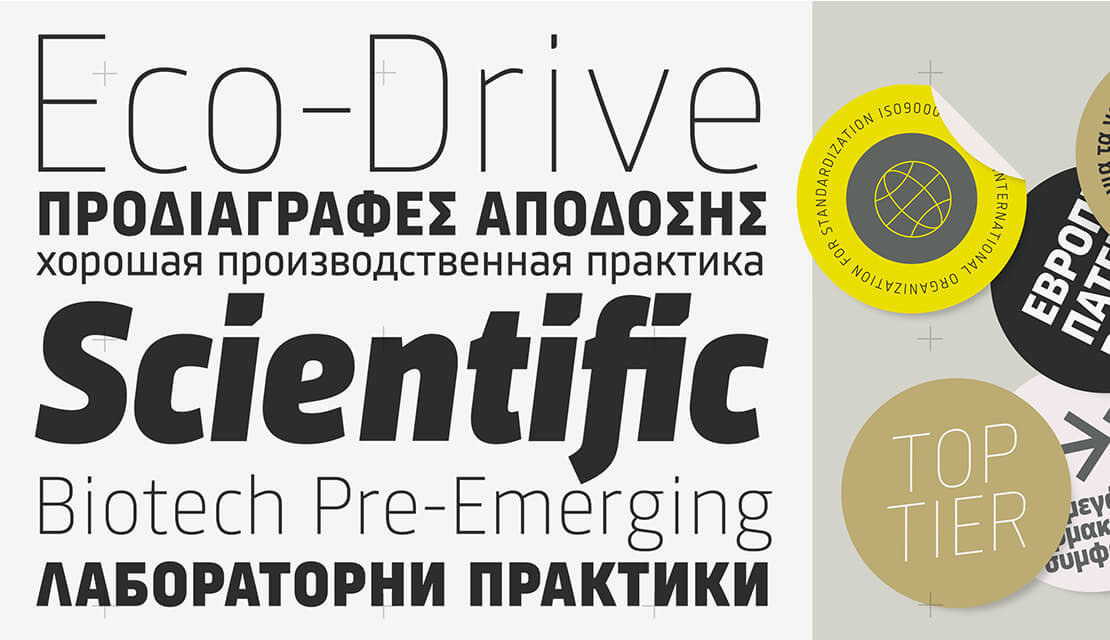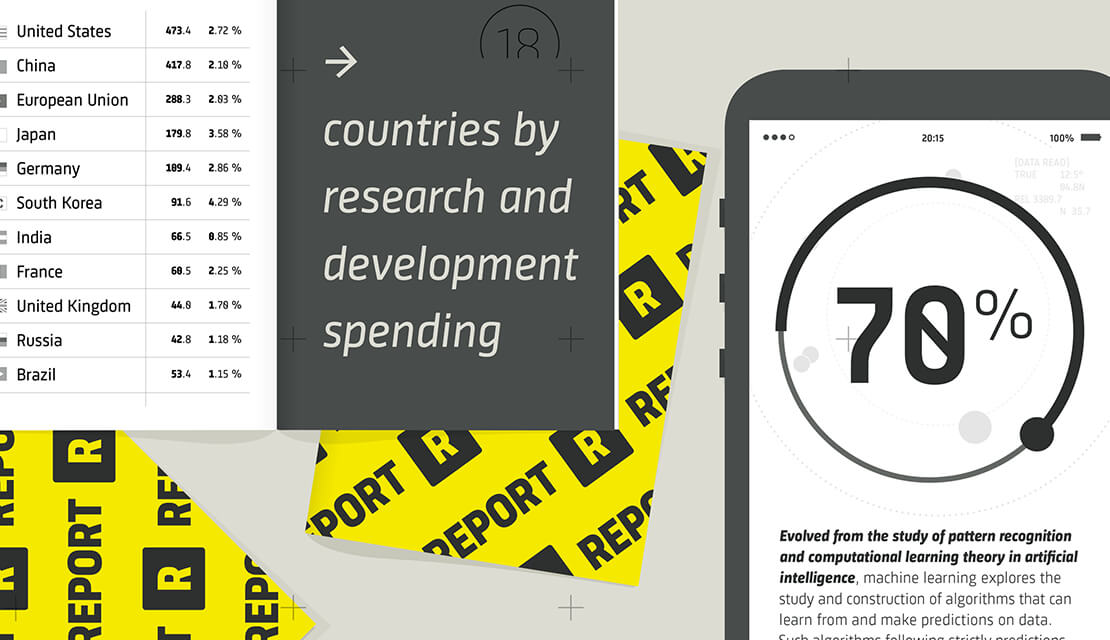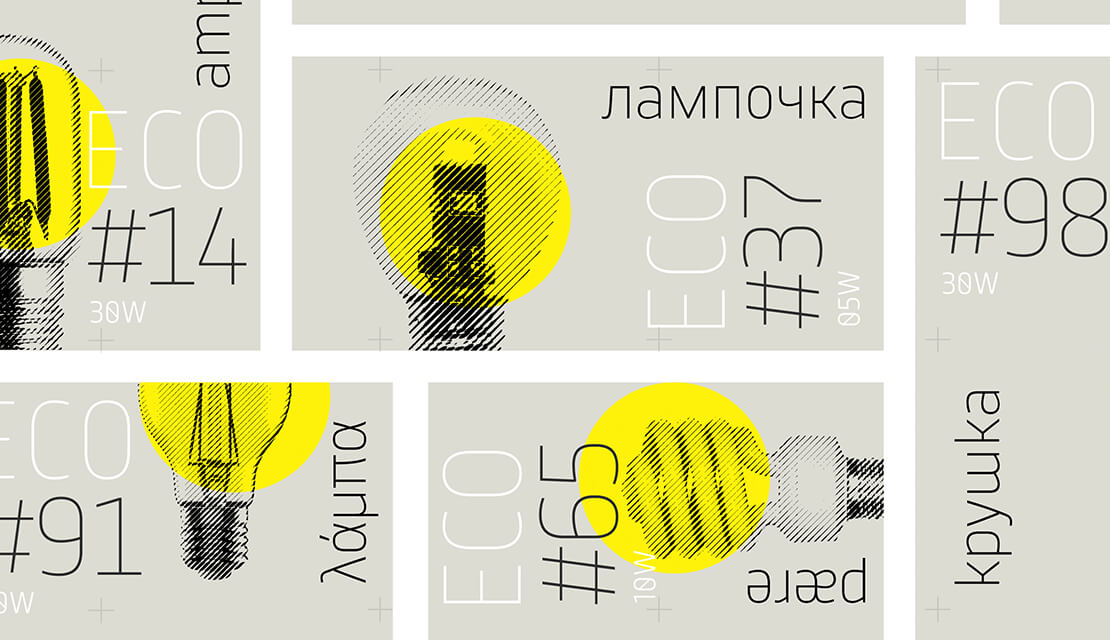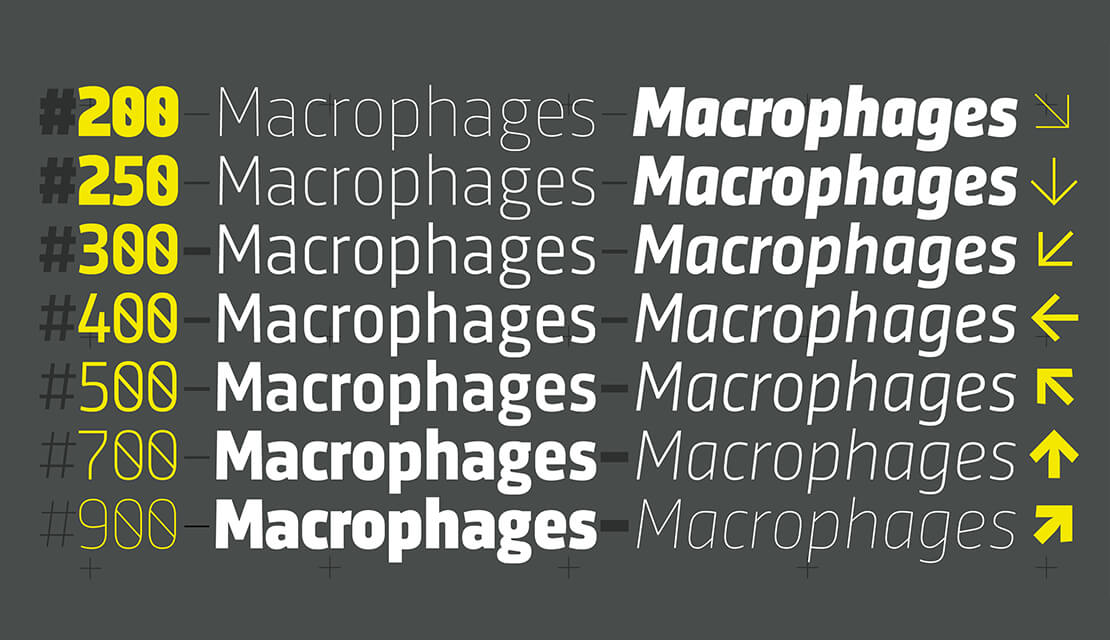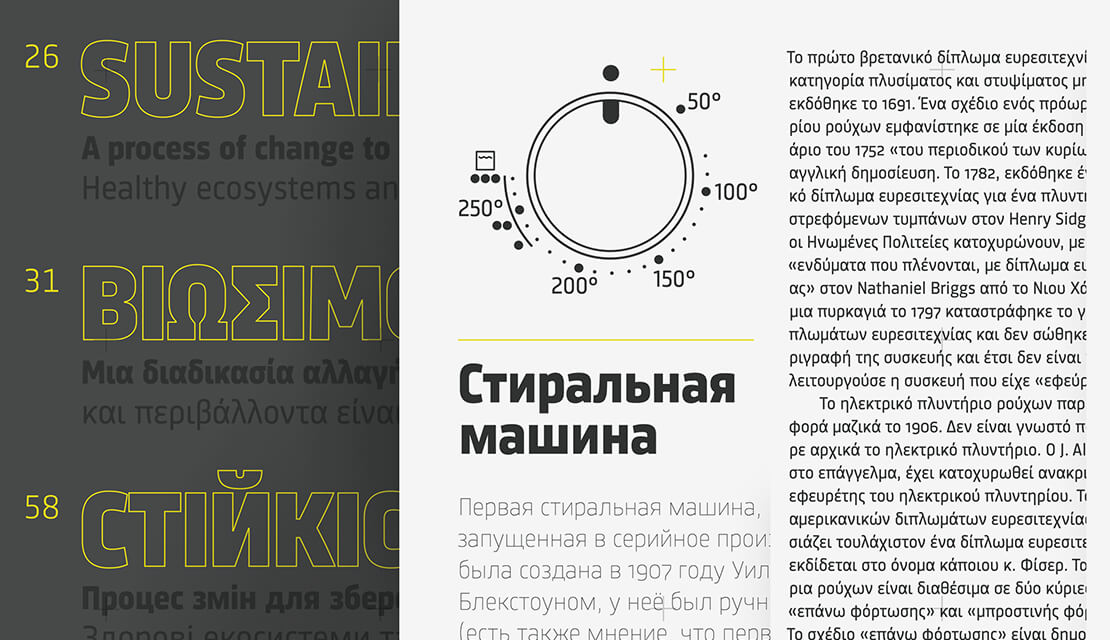
Neue Schrift für Interfaces: Sinews Sans Pro
Die Typemates haben »Sinews Sans Pro« herausgebracht. Die Schrift wurde ursprünglich 2012 für Marken eines Haushaltsgeräte-Herstellers veröffentlicht und nun umfassend renoviert.
Sinews Sans Pro Schrift
Entstehung der Sinews Sans Pro
Für viele Typedesigner ist das Design einer Schrift nie hundertprozentig fertig, nur akzeptabel genug um veröffentlicht zu werden. Aber manchmal werden Schrift-Designs auch wiederbelebt, wie die Geschichte der Sinews Sans zeigt, die für eine pan-Europäische Sprachunterstützung ausgebaut und neu gemastert wurde.
2017 hatten die Regional Marken bei BSH Hausgeräte GmbH Interesse an einer Schrift für das Interface– und Informationsdesign einer neuen Geräte-Kollektion. Für die TypeMates ein guter Anlass, sich wieder mit einem der ersten Entwürfe von Jakob Runge zu widmen: Die Sinews Sans wurde ursprünglich 2012 im Gestalten Verlag veröffentlicht. In Zusammenarbeit mit BSH Hausgeräte GmbH erfuhr sie eine umfassend Renovierung und beinhaltet jetzt unter anderem komplett neue Kurven und Bildschirmoptimierungen.
Sinews Sans Pro kursive Schnitte
Sinews Sans Pro als Schrift für Interfaces
Sinews Sans vereint in der Pro-Version moderne Proportionen und offene Formen einer technischen Sans mit organischen Elementen. Durch ihre Duplex-Funktion, in der jedes Zeichen die gleiche Breite in allen Gewichten und Stilen hat, kann die Schrift ganz einfach umformatiert werden, ohne dem Layout neue Zeilenumbrüche abzuverlangen.
Details mit kalligrafischen Ursprüngen werden das ansonsten klare und industrielle Design der Schriftart auf. In den subtilen Kurven der Kursiven wird das handschriftlich geprägte Grundgerüst erkennbar. Wie bei der Cera Pro bedient die Sinews Sans nicht nur die lateinischen Sprachen. Auch Griechisch und Kyrillisch inklusive der Alternativen für Bulgarisch, Mazedonisch und Serbisch werden abgedeckt.